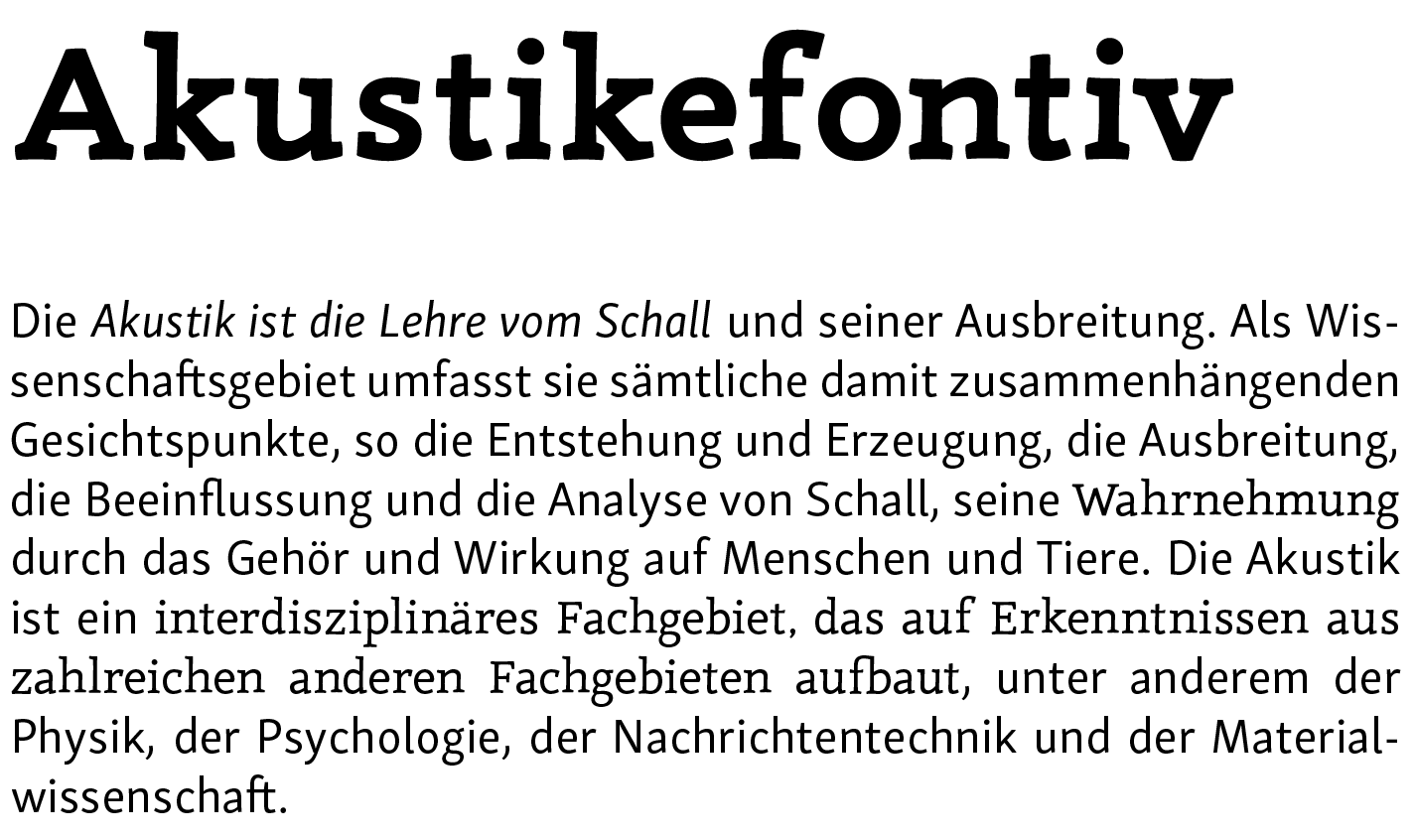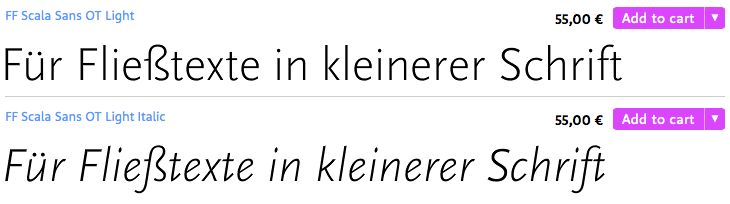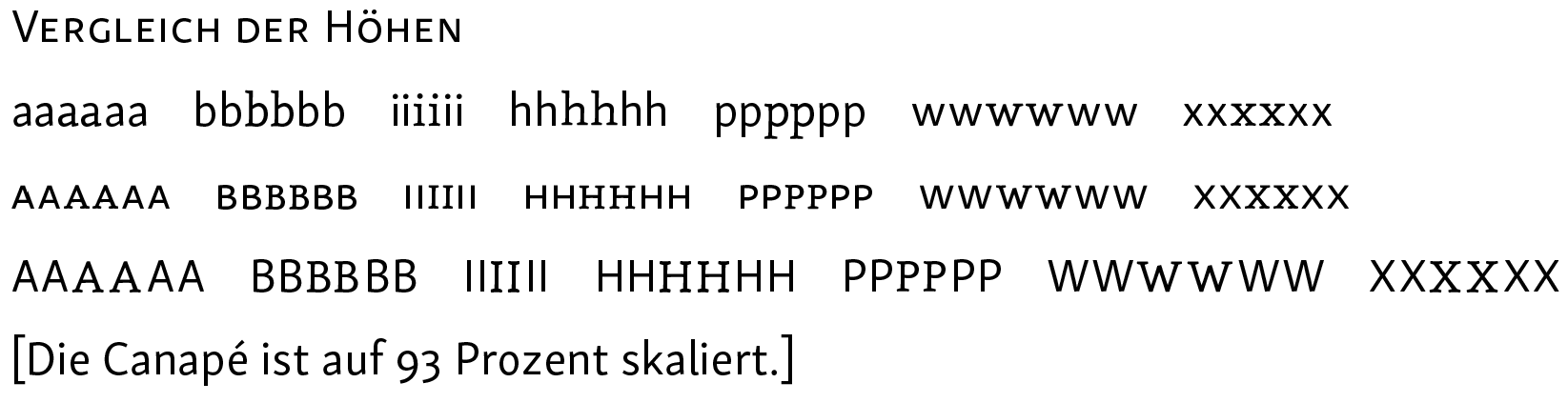
Scala Sans mit Canapé
ich bastle grad an meinem neuen CD und bin nun dabei, die Schriften festzulegen. Was haltet ihr von der Mischung der Scala Sans mit der Canapé? Ich würde letztere für Überschriften (und für die Wortmarke) und erstere als Brotschrift (und einen evtuellen Claim) verwenden, aber bei bestimmten Anwendungen das auch mal umdrehen. Eventuell ist es auch mal nötig, die eine als Auszeichnungsschrift innerhalb der anderen zu verwenden.
Die Canapé habe ich schon, die Scala Sans müsste ich mir noch kaufen, deswegen ist meine Wahl bisher noch nicht so ausführlich getestet – es ist mehr so ein Gefühlsding.
Hat jemand von euch beide Schriften und könnte mir mal ein Demo-PDF zusammen schustern, bitte?
Die Scala Serif würde ich eventuell später dazukaufen … das kann ich im Moment nicht alles auf einmal berappen. In dem Fall würde ich dann Scala Serif und Sans ganz klassisch kombinieren und die Canapé nur noch für Titel/Cover und Co. benutzen.
PS: Ist der Unterschied zumischen FF Scala Sans und FF Scala Sans Pro nur die Sprachabdeckung?
Was haltet ihr von der Mischung der Scala Sans mit der Canapé?
Kein schlechter Ansatz wie ich finde. Mir persönlich wäre die Scala Sans noch einen Hauch zu verspielt (a, w). Daher würde ich zur Canapé etwas ruhigeres suchen, damit sie als »Charakterdarsteller« besser zu Geltung kommt. Vielleicht etwas in der Richtung:
Kein schlechter Ansatz wie ich finde.
Die Freight sagt mit nicht so zu: Ich finde die etwas so „normal“ und die Kursive ist halt keine kursive, das mag ich auch nicht so. Die anderen finde ich aber sehr interessant und habe mir von allen mal die Test-PDFs gedruckt um sie morgen bei Licht zu begutachten.
Werde nachher oder morgen mal ein bisschen damit spielen … allerdings hab ich mich – insbesondere in die kursive – Scala Sans schon etwas verliebt …
Soooo … ich habe mal etwas verglichen sowohl Schriften als auch deren Preise, weil eben auch die leider ein Rolle spielen müssen. Deswegen habe ich die Kievit aussortiert; die ist im „Kilopreis“ einfach zu teuer. Für die vier verbliebenen Schriften habe ich für mich jetzt folgende, nicht endgültige, Präferenzreihenfolge festgelegt:
• Skolar Sans
• Scala Sans
• Seravek
• Alright Sans
Die Skolar gefällt mir tatsächlich besser als die Scala Sans und ist außerdem im „Kilopreis“ günstiger. Sie bietet wesentlich mehr Schnitte und ist auch besser ausgebaut scheint mir und die zugehörige Serif gefällt mir auch besser als die der Scala, was früher oder später eine Rolle spielen wird, wenn ich längere Texte veröffentliche. Ein weiteres Schmankerl der Skolar ist, dass sie genau wie die Canapé eine von der Form auch vergleichbare Th-Ligatur hat – auch wenn man die im deutschen kaum zu Gesicht bekommen wird …
Die Seravek ist, weil sie beim Mac dabei ist, preislich natürlich unschlagbar überzeugt mich ansonsten aber nicht so sehr. Zumal ich dann noch wieder eine passende Serif suchen müsste.
Die Alright hat auch keine Serif immerhin aber ne Slab, die Formen sind mir aber zu langweilig und wenig lebendig. Insbesondere die Kursive ist mir zu umeigenständig und sieht sehr nach „nur schräg gestellt“ aus.
Da es von der Skolar sogar zwei kostenlose Schnitte gibt, habe ich mir mal eine Test-PDF gebastelt. Ich finde Canapé und Skolar gehen ganz gut zusammen, auch wenn die Canapé im grauwert nen Hauch dunkler ausfällt. Damit kann ich leben, weil die beiden vermutlich nicht so häufig dicht beieinander stehen werden.
Mit einer Skalierung passen die Höhen der Groß- und Kleinbuchstaben auch zusammen – finde ich …
Hat jemand von euch zufällig die Scala Sans und die Canapé und könnte mir mein Test-PDF umsetzen? ID- (mit Absatzformaten) und PDF-Datei gibts hänge ich an.